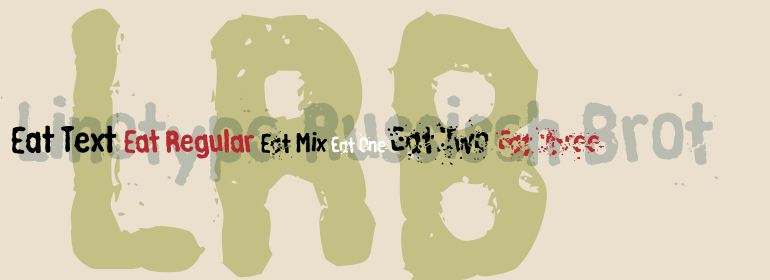
Linotype Russisch Brot™
Linotype Russisch Brot™,这款字体结构工整、笔画清晰,兼顾美观与易读性,适用于标题、正文、海报、包装、LOGO 等多种场景。字形优雅稳定,风格百搭耐看,适配日常排版与创意设计,让文字呈现更舒适、更具质感。Linotype Russisch Brot™一笔一画,皆是细节,以均衡的比例、流畅的线条打造舒适视觉体验,字形端正大气,风格简约现代。无论是商业设计、品牌宣传还是日常排版,都能轻松驾驭,让文字更有格调与力量。Linotype Russisch Brot™字体下载。
字体品牌: Linotype(Monotype) 设计师:Ness,Helmut; Remscheid,Markus 字体分类:衬线体 字体属性:外文 字符集:Unicode 发布时间: 2018